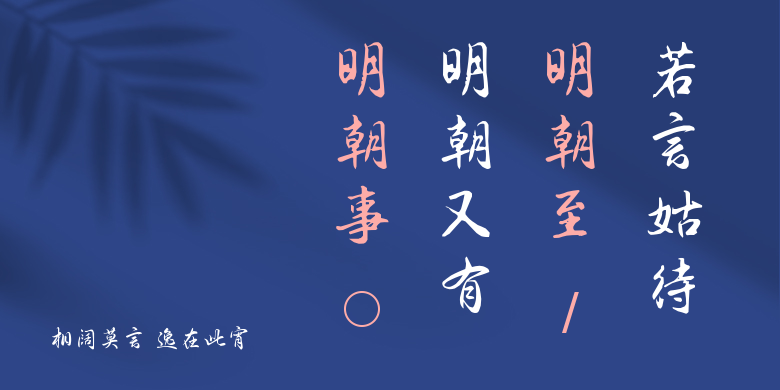
相阔莫言 逸在此宵
相阔莫言 逸在此宵,这款字体结构工整、笔画清晰,兼顾美观与易读性,适用于标题、正文、海报、包装、LOGO 等多种场景。字形优雅稳定,风格百搭耐看,适配日常排版与创意设计,让文字呈现更舒适、更具质感。相阔莫言 逸在此宵一笔一画,皆是细节,以均衡的比例、流畅的线条打造舒适视觉体验,字形端正大气,风格简约现代。无论是商业设计、品牌宣传还是日常排版,都能轻松驾驭,让文字更有格调与力量。相阔莫言 逸在此宵字体下载。